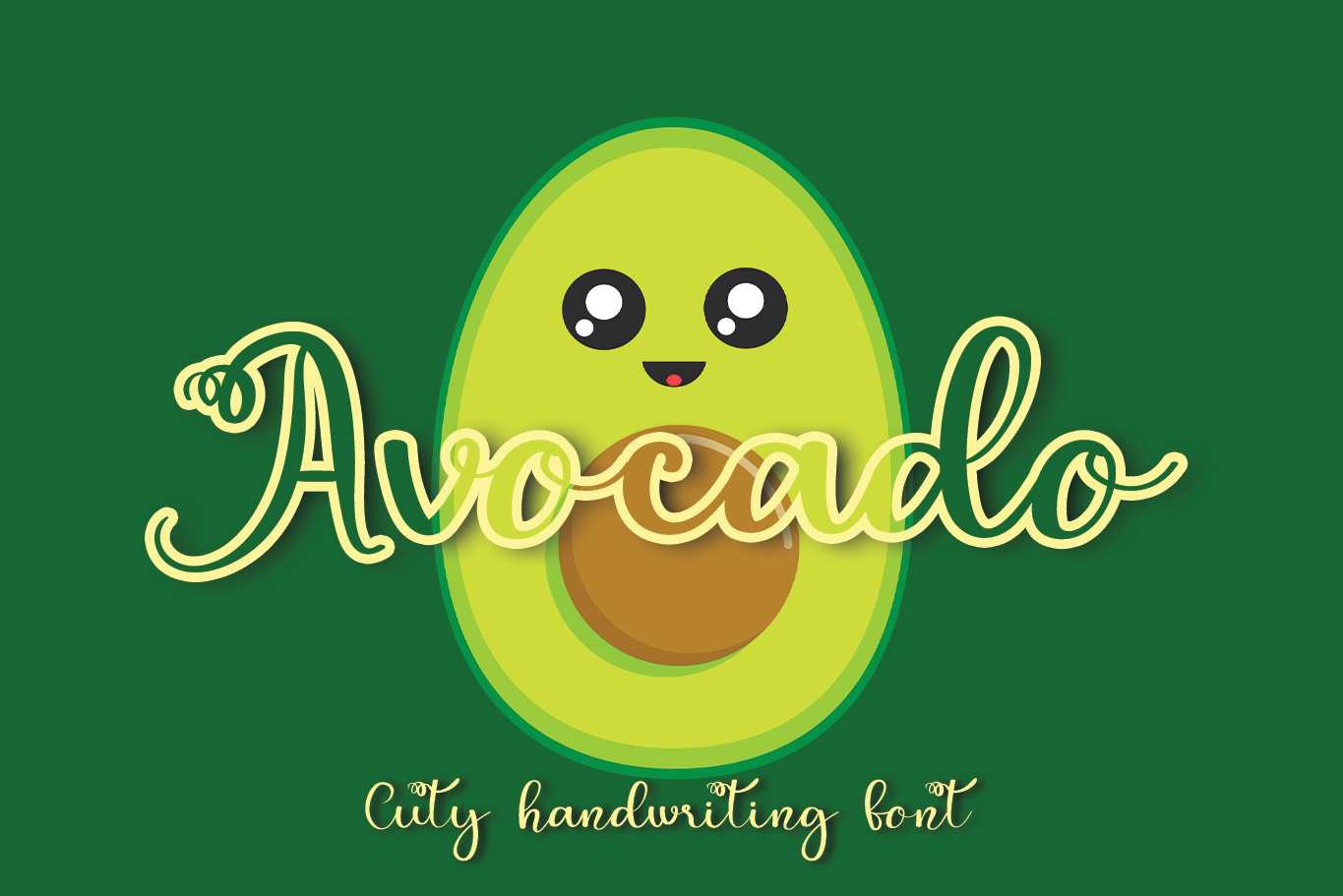
Avocado Font – Download Grátis
A Avocado Font é uma elegante tipografia script moderna criada por el hotcig. Com seu ar delicado e charmoso, esta fonte traz alegria e romantismo aos projetos mais variados. Seja você um designer de revistas, uma empresa de moda ou um artista gráfico, ela atende às necessidades de cada trabalho, tornando cada projeto único e especial. Com sua escrita suave e refinada, Avocado Font é o escolher-se ideal para quem busca algo delicado mas sofisticado para adicionar aos seus designes. Não importa qual ideia de design você tenha em mente, a Avocado Font certamente será uma opção adequada.
Designer: el hotcig